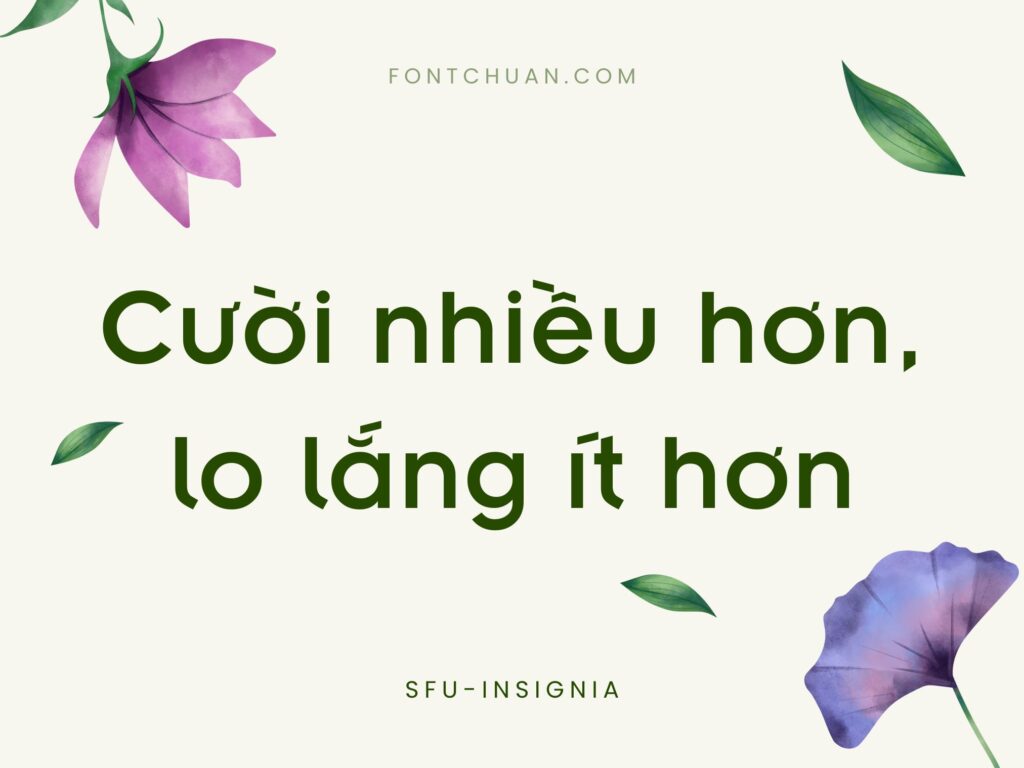
Insignia là một kiểu chữ sans-serif được thiết kế bởi Neville Brody vào năm 1986, ban đầu dành cho tạp chí Arena và sau đó được phát hành thương mại bởi Linotype vào năm 1989. Font này được sưu tầm và đăng bởi thành viên của Font Chuẩn. Insignia nổi bật với thiết kế hiện đại, các đường nét rõ ràng và độc đáo, phù hợp cho nhiều mục đích sử dụng khác nhau.
Về mặt thiết kế, Insignia có các đường nét gọn gàng, tỷ lệ cân đối và độ tương phản thấp, tạo cảm giác thanh lịch và chuyên nghiệp. Font này hỗ trợ nhiều ngôn ngữ và bao gồm các ký tự đặc biệt, giúp người dùng dễ dàng tùy chỉnh theo nhu cầu. Insignia thường được sử dụng trong các thiết kế đồ họa, in ấn, biển hiệu và nhận diện thương hiệu. Các ngành nghề như quảng cáo, công nghệ, giáo dục và bất động sản có thể tận dụng kiểu chữ này để tạo dấu ấn đặc biệt trong truyền thông.